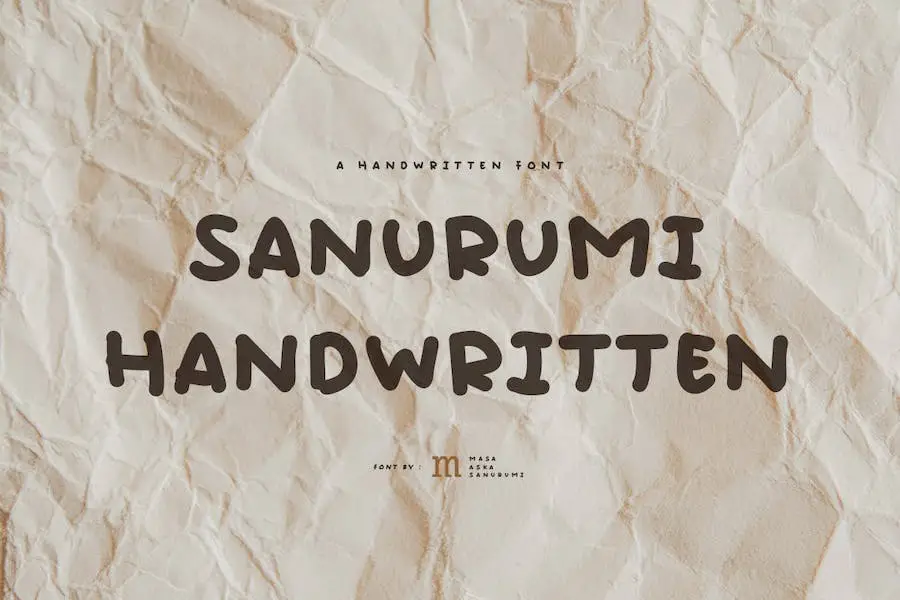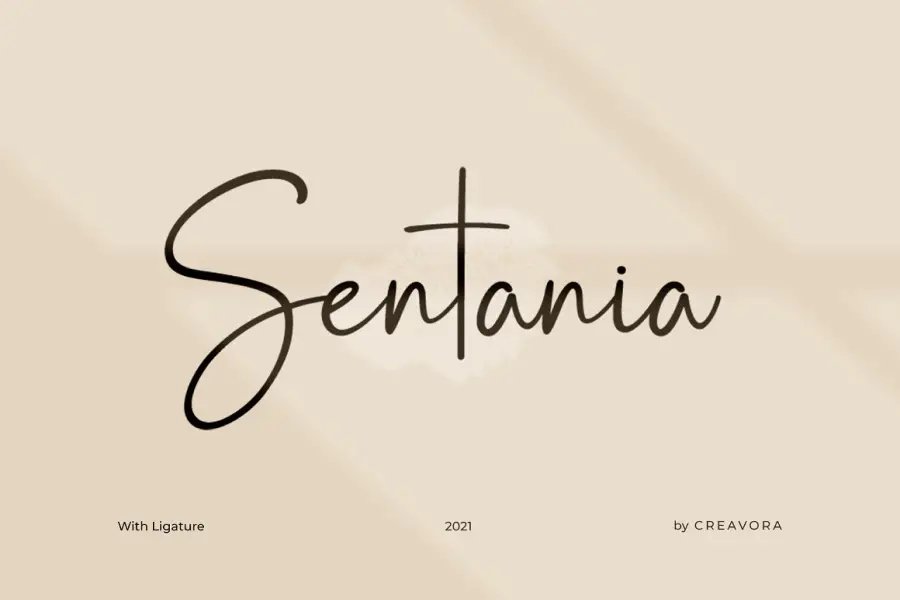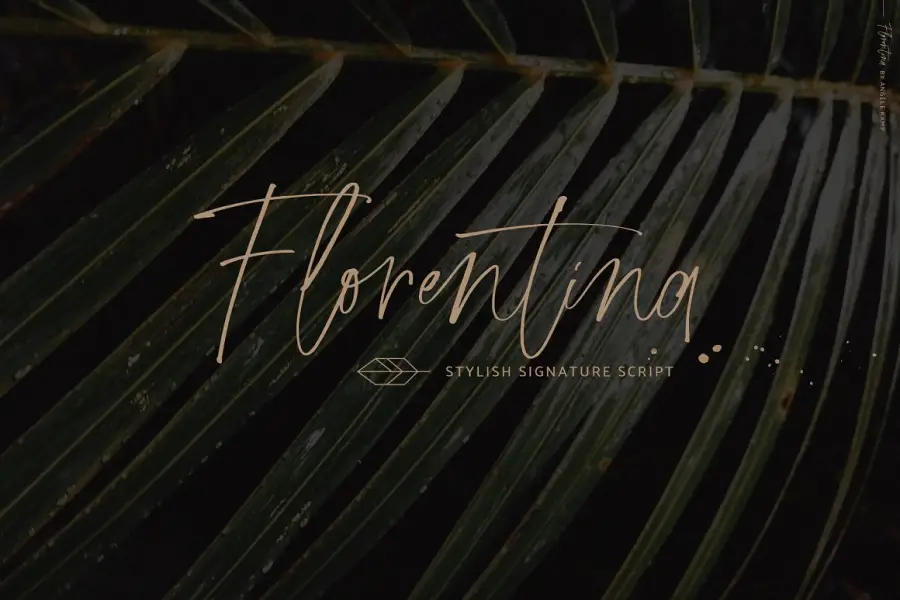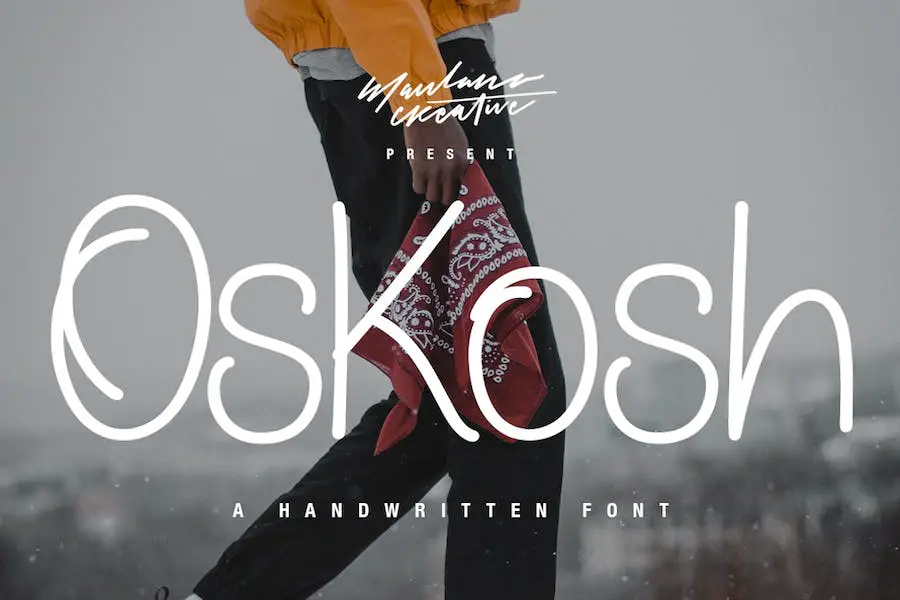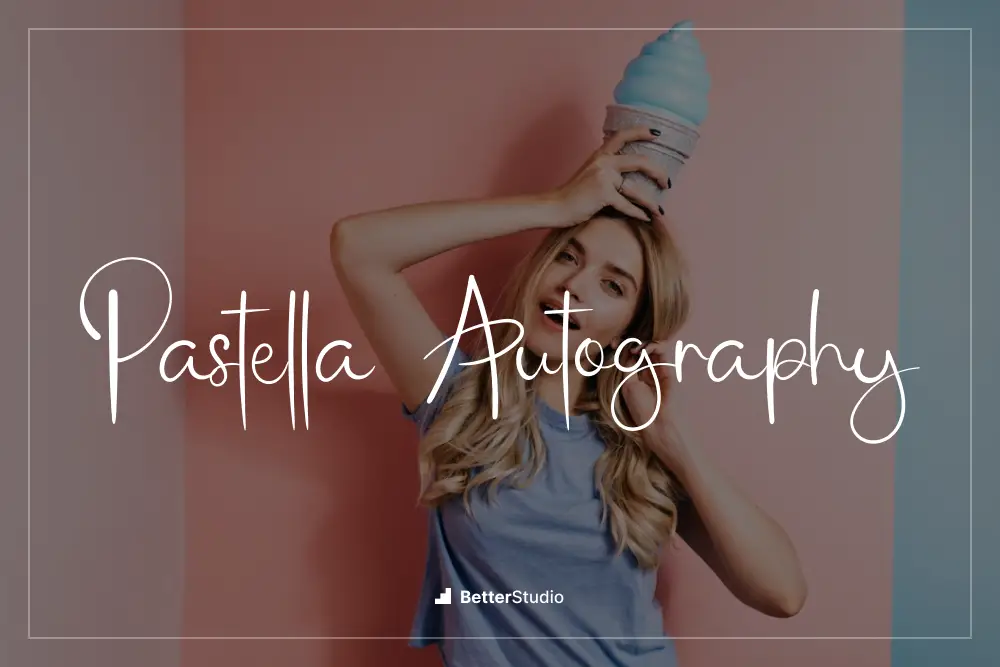
15 cele mai bune fonturi scrise de mână ️ 2023 (gratuit și pro)
Publicat: 2023-04-30Te-ai trezit vreodată defilând prin opțiunile de font ore în șir, încercând să-l găsești pe cel perfect pentru proiectul tău?
Dacă da, nu ești singur! Alegerea fontului potrivit poate face diferența în designul sau lucrarea scrisă. De aceea am întocmit această listă cu „15 cele mai bune fonturi scrise de mână”.
În acest articol, vom discuta despre primele 15 fonturi scrise de mână care vor adăuga cu siguranță o notă unică și personală oricărui proiect.
Știați că s-a dovedit că fonturile scrise de mână măresc implicarea și lizibilitatea în conținutul scris? Ele ajută la transmiterea personalității și emoțiilor, făcându-le o alegere populară pentru orice, de la invitații la grafica social media.
Fie că doriți să adăugați un pic de fler site-ului dvs. sau pur și simplu doriți să vă îmbunătățiți următorul proiect, aceste fonturi vă vor inspira cu siguranță.
Așa că, fără alte prelungiri, să ne aruncăm în lista noastră cu cele mai bune 15 fonturi scrise de mână!
Cele mai bune fonturi premium scrise de mână
În această postare, vom discuta despre cele mai bune fonturi premium scrise de mână care vă pot ajuta să vă ridicați proiectele de design la nivelul următor. Fiecare font are propriul stil și personalitate unică, așa că fie că proiectați un logo sau creați materiale de marketing, există ceva pentru toată lumea.
Deci, fără alte prelungiri, haideți să ne aruncăm în lista noastră cu cele mai bune fonturi premium scrise de mână!
Oh, perie Livey
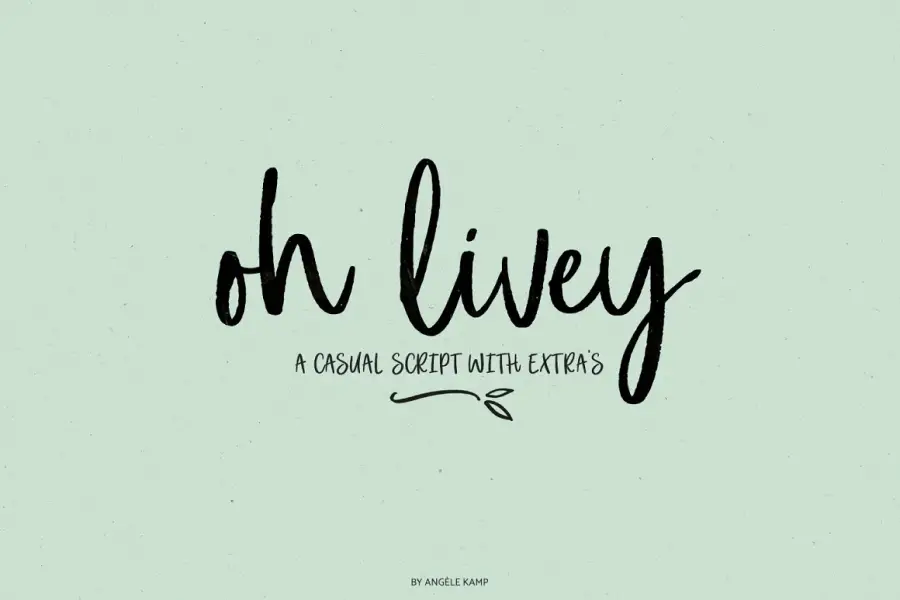
Oh Livey brush este un font elegant și jucăuș, care este perfect pentru a adăuga o notă modernă design-urilor tale. Acest font de tip perie este versatil și poate fi folosit în diverse scopuri, de la citate la site-uri web. De asemenea, este potrivit pentru fonturile scrise de mână Google.
Una dintre caracteristicile remarcabile ale Oh Livey este gama sa extinsă de ligaturi, care conferă fontului un aspect autentic scris de mână. Cu aceste ligaturi, puteți crea modele frumos lucrate care par să fi fost desenate manual de un artist.
O altă caracteristică excelentă a lui Oh Livey este clipart-ul suplimentar care vine cu fontul. Clipart face proiectarea și mai distractivă și fără efort, permițându-vă să adăugați o notă de creativitate proiectelor dvs. cu ușurință.
Bisyk scris de mână
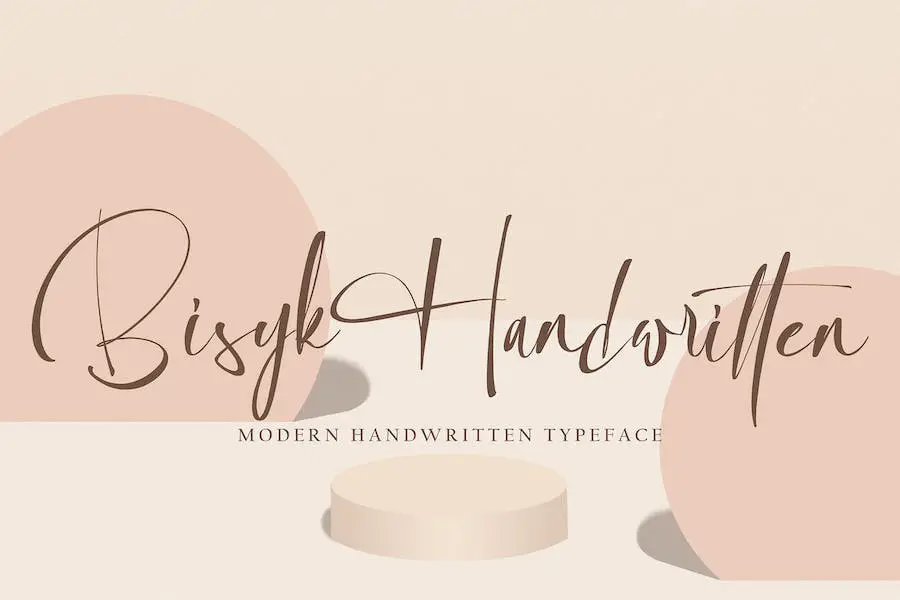
Bisyk Handwritten este un font care are un stil nou și poate fi folosit pentru diverse proiecte, cum ar fi citate, logo-uri, anteturi de blog, postere, branding, scrisori, invitații și articole de papetărie. Acest font va adăuga o notă unică și personală oricărui proiect la care lucrați.
Fontul Bisyk Handwritten are un aspect scris de mână care este atât elegant, cât și ușor de citit. Fontul vine în diferite greutăți, permițându-vă să-l alegeți pe cel perfect pentru proiectul dvs. Îl puteți folosi pentru titluri sau textul corpului și se potrivește bine cu alte fonturi. De asemenea, puteți utiliza acest font scris de mână pentru cuvânt.
Awesomepilll
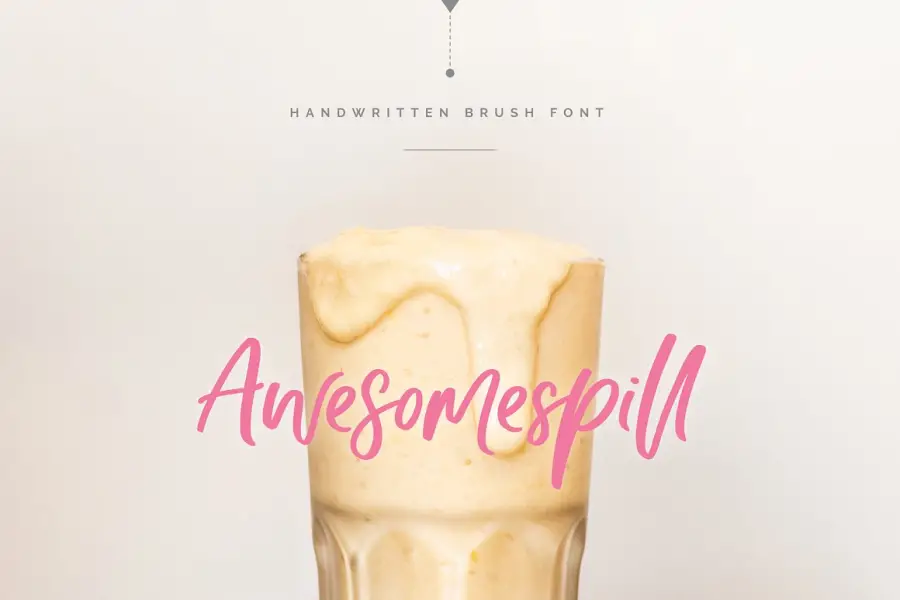
Awesomespill este un font de tip perie interesant, perfect pentru o varietate de utilizări. Realizat cu mare grijă și atenție la detalii, acest font are o senzație suculentă, scrisă de mână, care va face ca siglele, titlurile, ambalajul produselor, mărfurile și citatele dvs. să iasă în evidență din mulțime.
Unul dintre lucrurile care face ca Awesomespill să fie atât de unic este setul complet de litere mici alternative și 21 de ligaturi care vin cu el. Acest lucru vă oferă o mulțime de opțiuni cu care să vă jucați, asigurându-vă că fiecare design pe care îl creați cu acesta este complet original și unic.
Burdown scris de mână
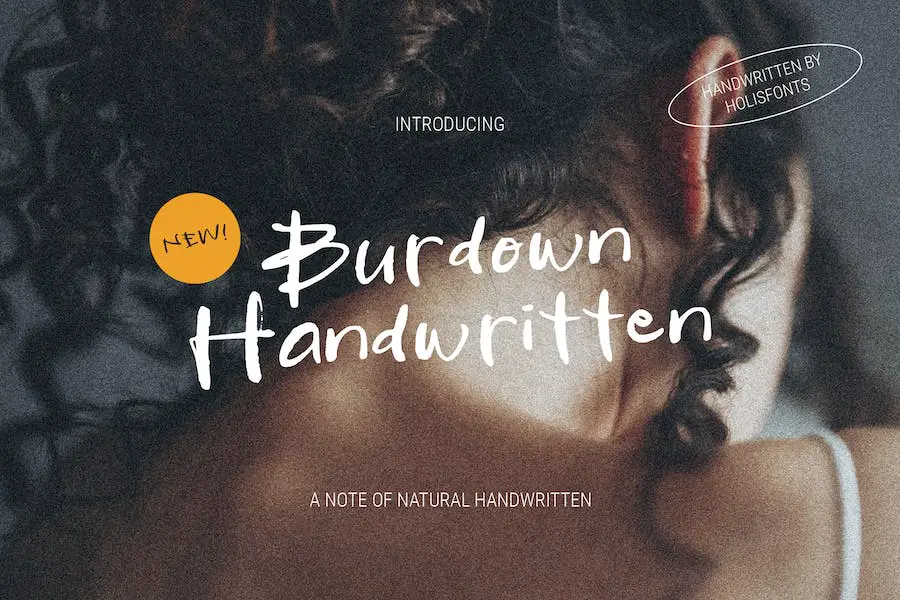
Burdown Handwritten este un font care va oferi design-urilor tale o senzație naturală și realistă. Dacă sunteți în căutarea unui font scris de mână aspru și dezordonat, atunci acesta este cel potrivit pentru dvs. Cu stilul său unic, Burdown Handwritten va face modelele tale să iasă în evidență din mulțime.
Una dintre cele mai bune caracteristici ale Burdown Handwritten este aspectul său autentic. Are aspectul unui scris de mână real, care va adăuga o notă organică desenelor tale. Îl puteți folosi pentru o varietate de proiecte, cum ar fi logo-uri, invitații, postere și multe altele. Versatilitatea sa îl face un plus excelent pentru colecția oricărui designer.
Lady Clementine
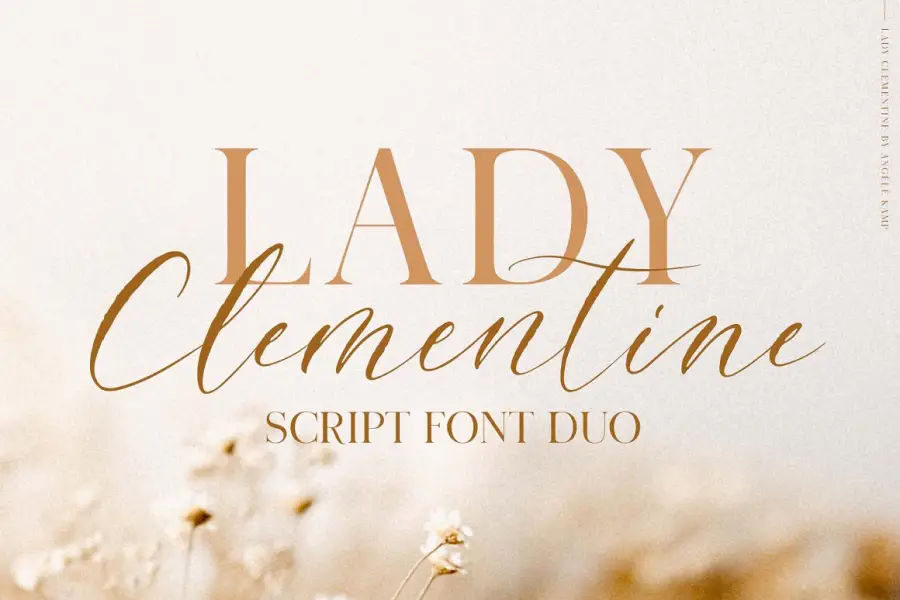
Lady Clementine este unul dintre fonturile cursive și o combinație uimitoare de două fonturi, un script frumos și un serif elegant care va ridica orice proiect de design. Fontul script are o textură de caligrafie modernă, dându-i o senzație naturală de scris de mână. Fontul serif completează perfect scriptul, făcându-l duo-ul ideal pentru invitații de nuntă, logo-uri și branding.
Acest duo atemporal de fonturi de nuntă emană stil și sofisticare care nu pot fi ratate în colecția ta de fonturi. Lady Clementine este perfectă pentru cei care doresc să adauge o notă de lux și eleganță design-urilor lor. Combinația dintre fonturile script și serif creează o armonie frumoasă, asigurându-vă că modelele dvs. sunt atât elegante, cât și feminine.